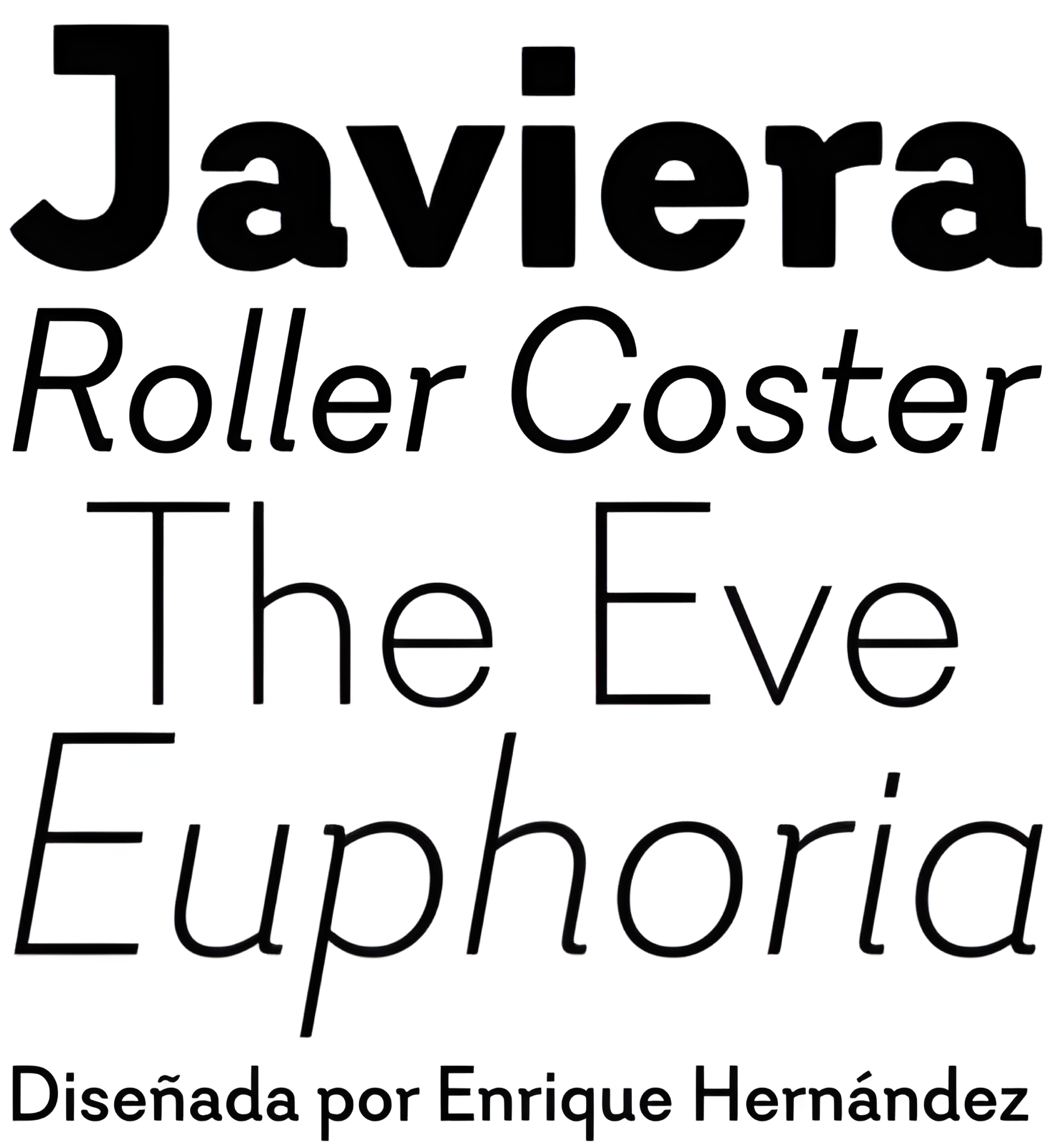
| Año | 2017 |
| Créditos | Enrique Hernández |
| Descripción | Javiera es un tipo de letra geométrica sin gracias con atributos humanistas. Una de sus principales características es su pequeña altura x, que hace que los ascendentes y descendentes parezcan más largos. El contraste da a la fuente un aspecto más estilizado, típico de las fuentes humanistas. Las curvas y los terminales redondeados hacen de Javiera un tipo de letra suave, amable y versátil, muy adecuado para marcas, revistas y proyectos editoriales. El usuario puede sacar más partido de la versatilidad de la fuente habilitando los caracteres alternativos incluidos en el conjunto. Javiera se presenta en 6 estilos -desde Thin hasta Black-, además de cursivas a juego, lo que da un total de 12 fuentes. Los pesos extremos de la fuente son perfectos para su uso en pantalla. La familia Javiera contiene un conjunto de más de 400 caracteres y es compatible con más de 200 idiomas diferentes. |